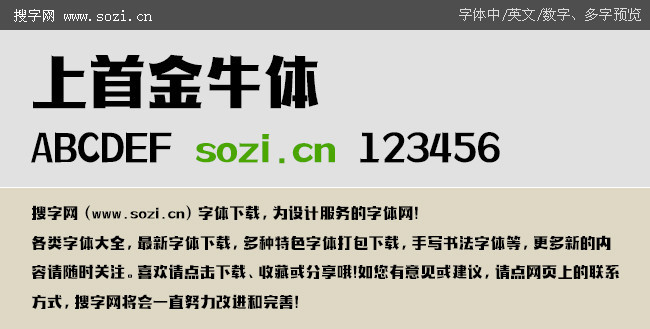
上首金牛體
搜字網(wǎng)給大家提供一款上首金牛體中文字體下載,上首金牛體字體筆畫(huà)橫細(xì)豎粗,橫豎筆劃增加了突出的尖角,整體字形方正,具有穩(wěn)重沉穩(wěn)的風(fēng)格。字體整體簡(jiǎn)約時(shí)尚,現(xiàn)代感十足。適用于搭配標(biāo)志、廣告標(biāo)語(yǔ)、商業(yè)廣告等廣告設(shè)計(jì)。